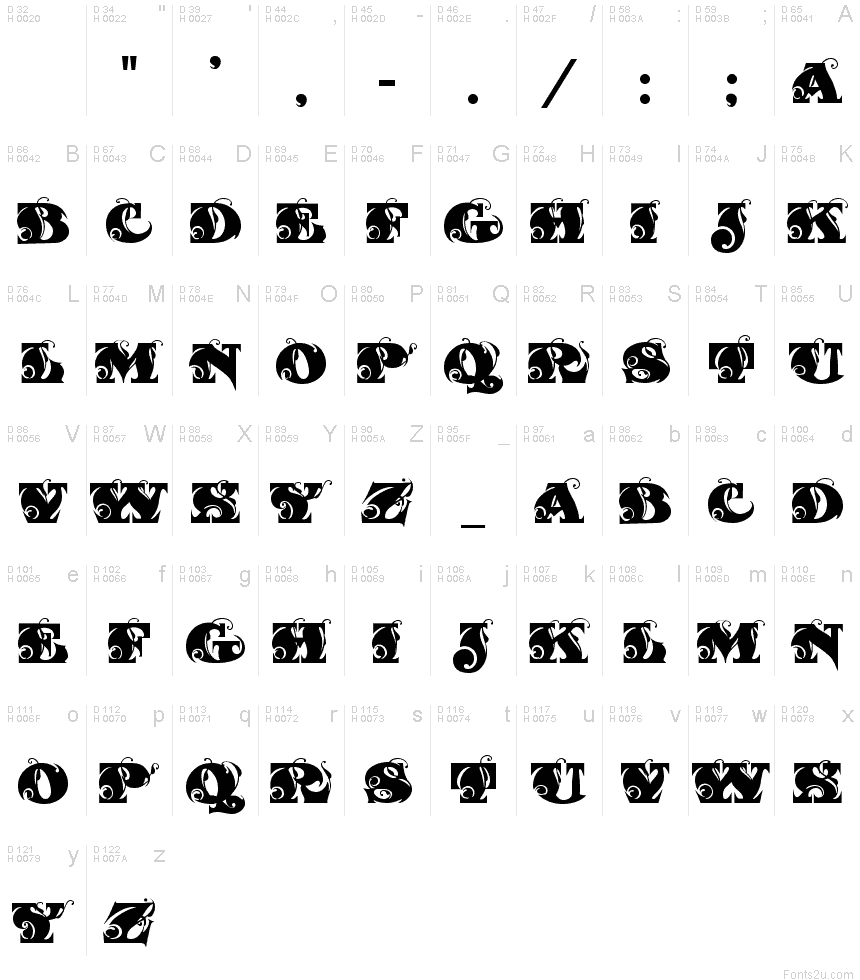
Fantastic MF Initials di Richard William Mueller è un carattere display decorativo gratuito che trasforma ogni lettera in una piccola opera d'arte fantasy. Blocchi neri pieni creano silhouette drammatiche, mentre dettagli bianchi nitidi e viticci intrecciati si snodano tra le forme come una filigrana a inchiostro. È audace e ornamentale al tempo stesso, regalando quel tocco gotico fiabesco senza perdere leggibilità nei contorni principali.
Con Fantastic MF Initials, basta poco: usala in grande per iniziali, loghi o titoli brevi e lascia che siano le volute a parlare. Questo font gratuito è perfetto per copertine di libri fantasy, titoli di giochi, inviti a eventi magici, packaging di boutique e locandine teatrali. Per il testo di supporto, abbinala a un sans serif geometrico pulito per mantenere l'attenzione su quelle forme scolpite e ricche.